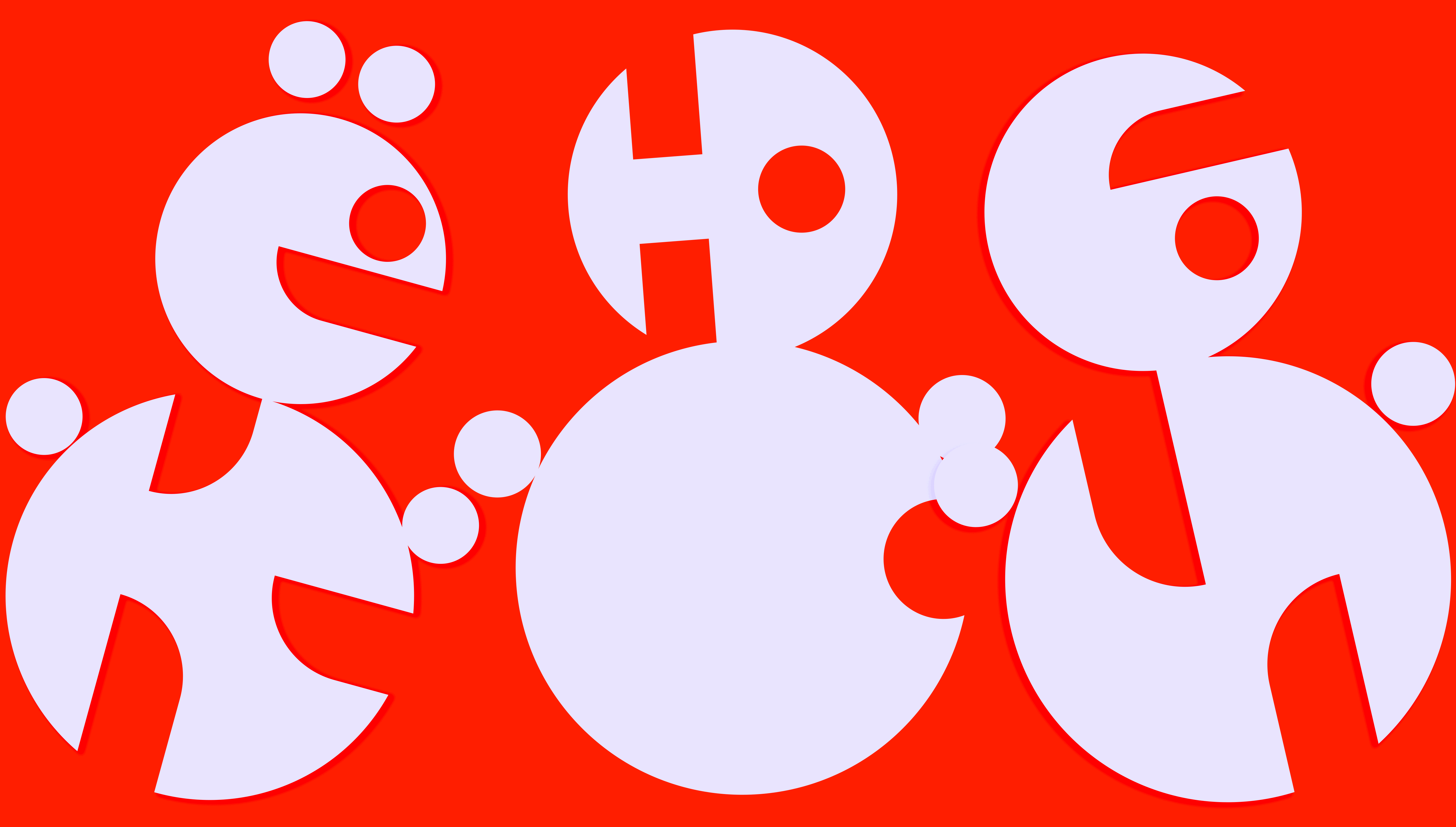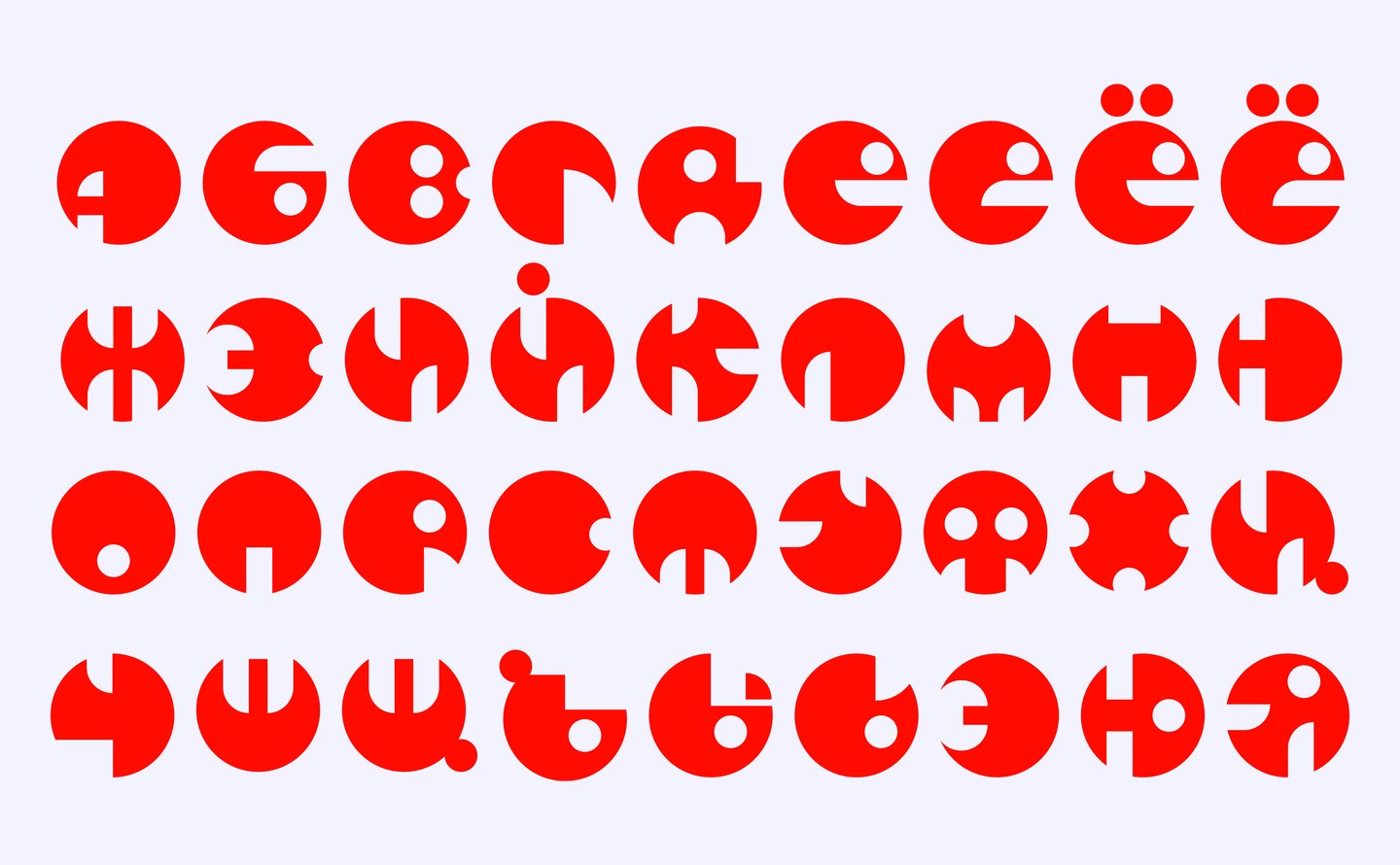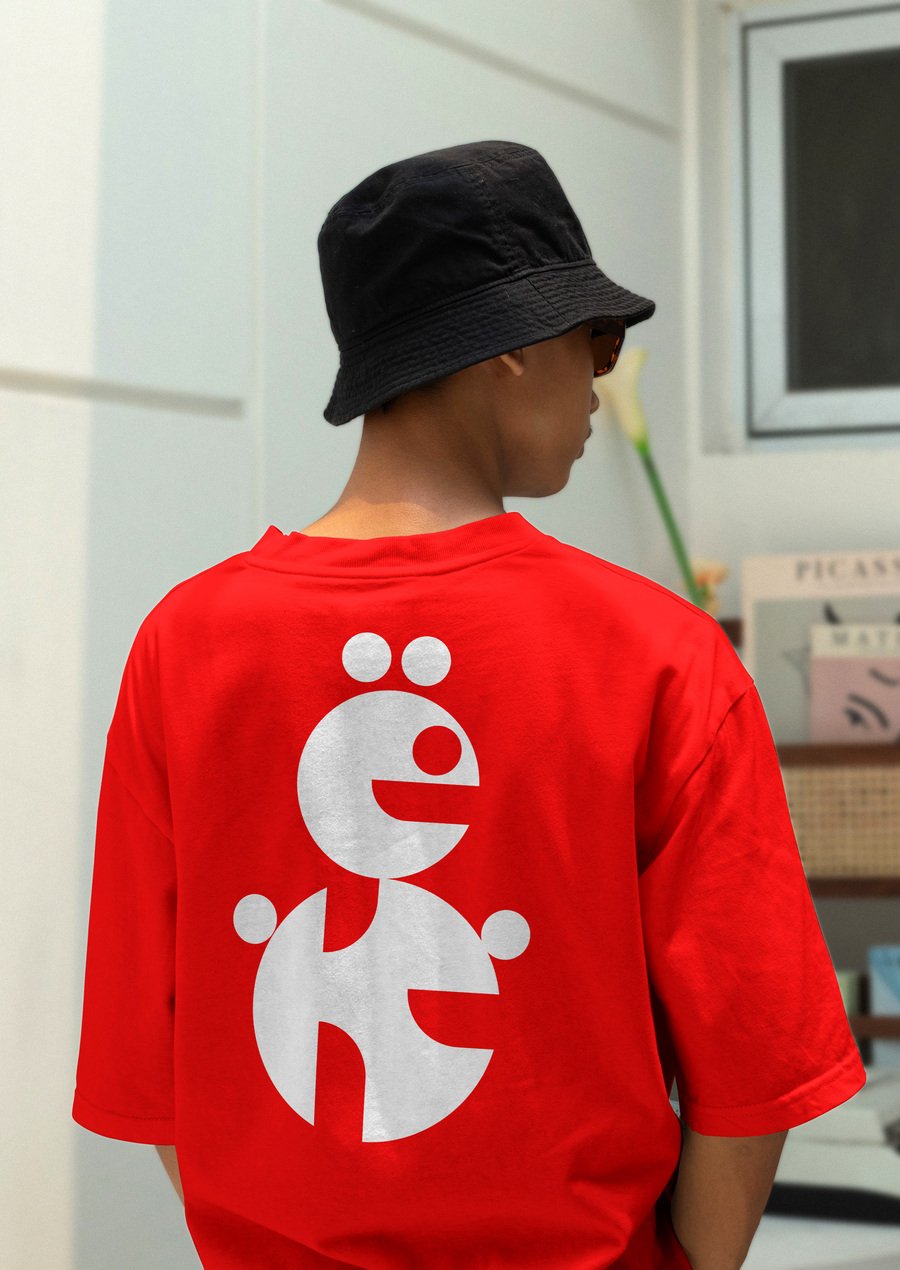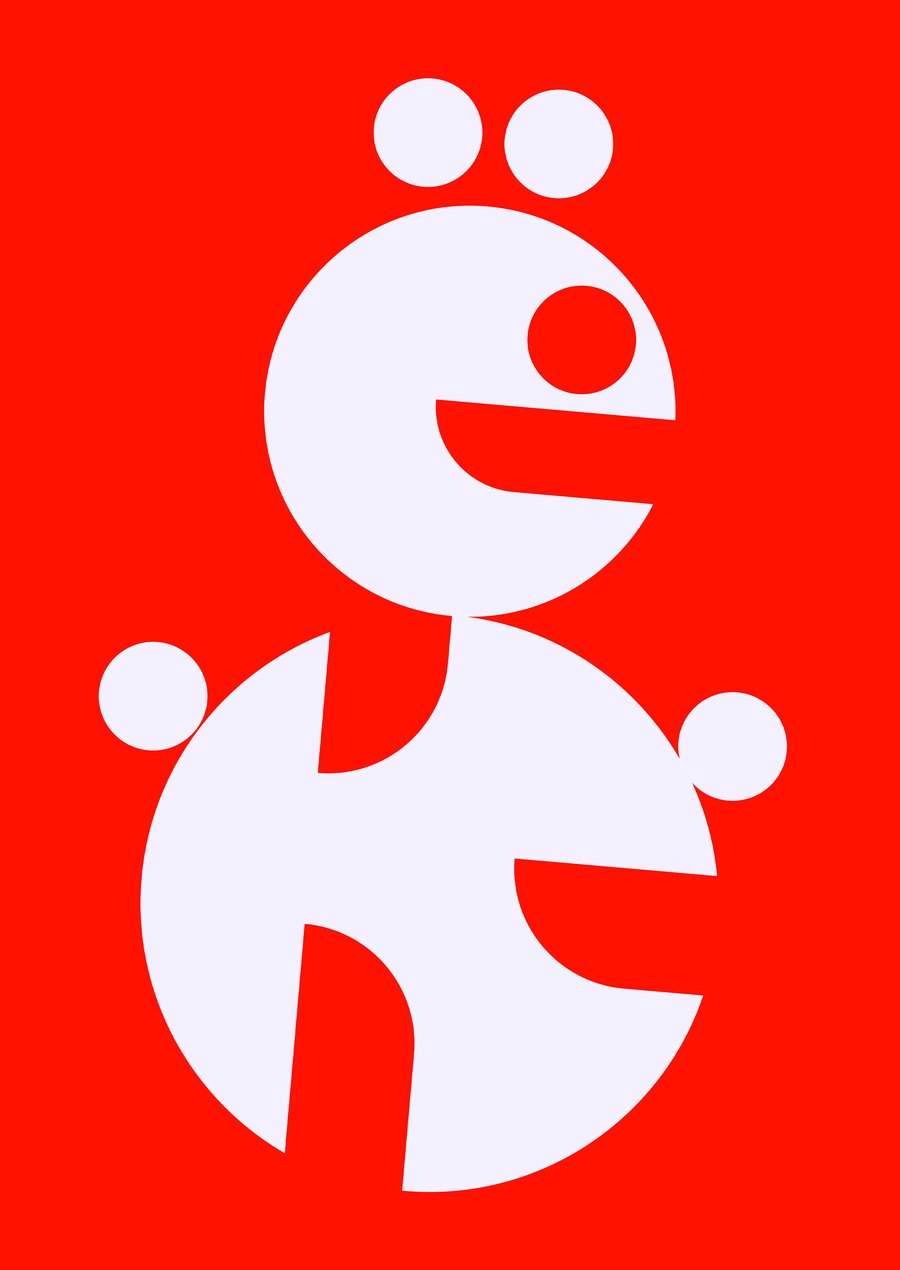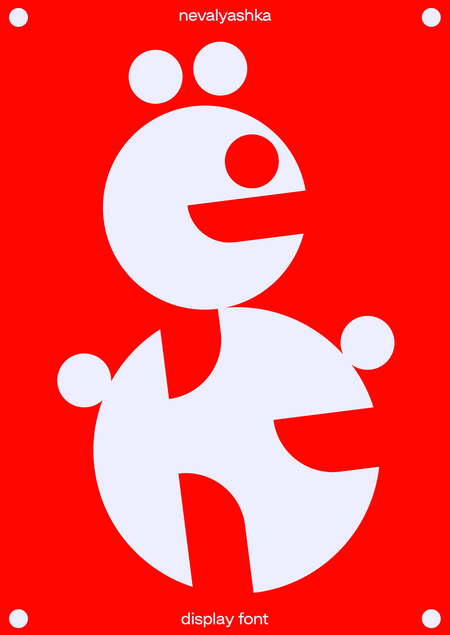
Nevalyashka typeface это модульный шрифт, который переосмысляет образ классической неваляшки. Он отсылает к азиатскому монаху, телесно разрушенному медитацией и превращённому в сакральный объект. В шрифте сочетаются русская округлая устойчивость неваляшки и азиатская ритуальная острота формы. Он балансирует между детской формой и жестокой историей, превращая типографику в акт уважения к источнику.
кириллица
кириллица — три начертания
тонкое начертание
латиница
цифры и доп.символы